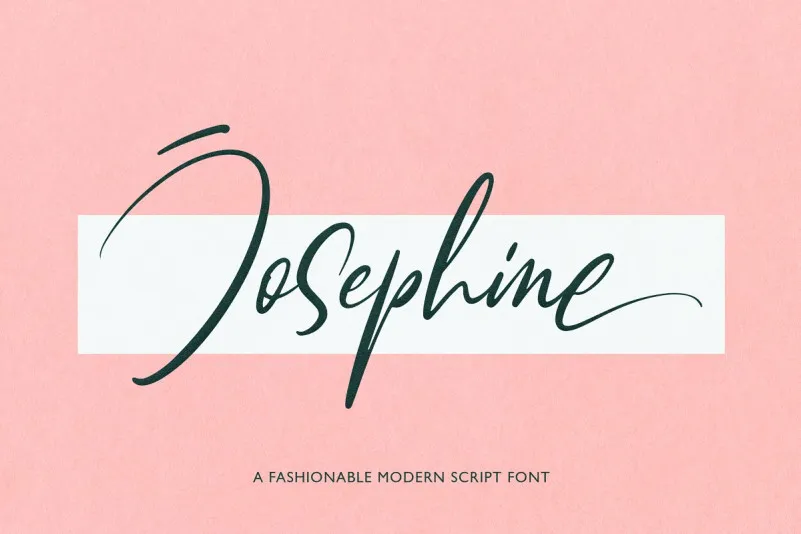
Bem-vindo ao catálogo de nossas Fonts de Script! Se você é fã de letra cursiva, a fonte Josephine está aqui para deixar seu design ainda mais especial e original. Essa moderna e elegante font foi criada pelo designer 178-MC e é perfeita para quem quer dar um toque único às suas criações. Josephine oferece uma diversidade de alternativas, ligaturas e alinhamentos contextualizados que adicionam profundidade aos seus trabalhos, tornando-os ainda mais autênticos. Esta font contém 70+ ligaturas, alternativas contextuais e alternativas estilísticas que permitem ao designer explorar completamente suas possibilidades. Ideal para um toque de personalização a qualquer design, Josephine está aqui para transformar sua arte digitais em algo realmente único e sofisticado. Descubra como ela pode tornar seu trabalho ainda mais impressionante!